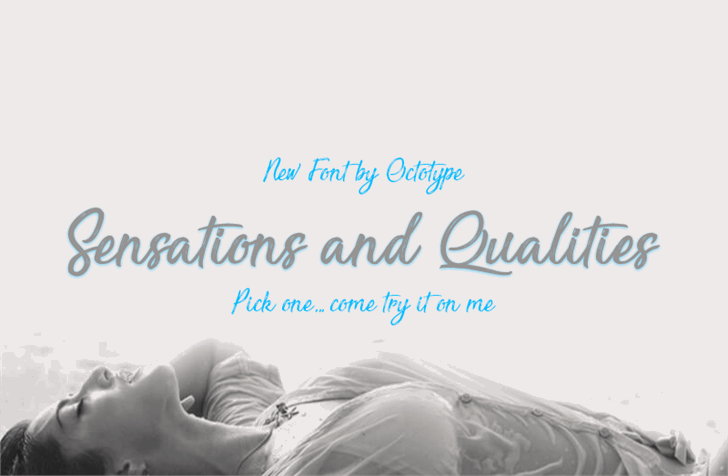
Sensations and Qualities Font – Fonte Grátis
Sensations and Qualities Font
A Sensations and Qualities Font é uma elegante escolha para designers que procuram uma fonte brush com um toque sofisticado, ideal para criar efeitos visuais intrigantes. Esta fonte foi criada pelo Octotype e oferece tanto o Full Font quanto a licença comercial de uso em seu catálogo. Para aqueles interessados no design gráfico ou que desejam incorporar uma personalidade única às suas criações digitais, esta font pode ser a solução perfeita. Se você está buscando algo além do básico e está pronto para explorar nuances criativas, o Octotype Sensations and Qualities Font é certamente para você. Para obter mais informações ou fazer um download, basta entrar em contato através do endereço de e-mail fornecido.